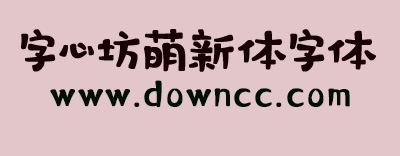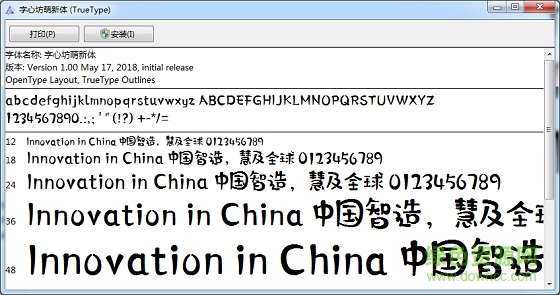
字心坊萌新ttf是一個免費的藝術(shù)字體。這款字體很受萌妹子們的喜愛,外形萌萌的,在平面設(shè)計行業(yè)使用的非常廣泛。能夠在win7、win8等主流操作系統(tǒng)上安裝使用!歡迎下載體驗。
字心坊萌新字體外形結(jié)構(gòu)圓潤可愛,字形活潑清新,具有很強的視覺效果,可適合應用于藝術(shù)設(shè)計、平面宣傳設(shè)計、網(wǎng)頁設(shè)計等領(lǐng)域!喜歡的網(wǎng)友快來綠色資源網(wǎng)下載吧!